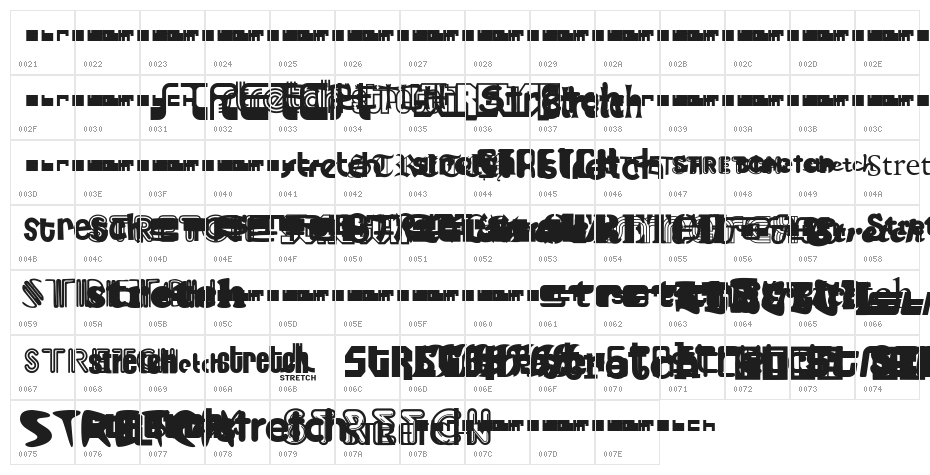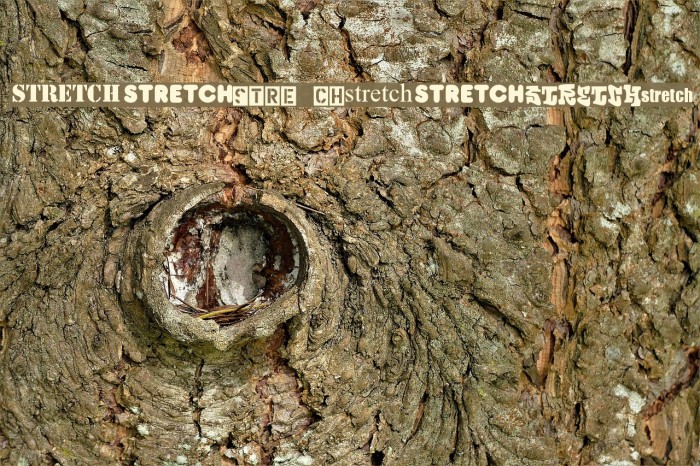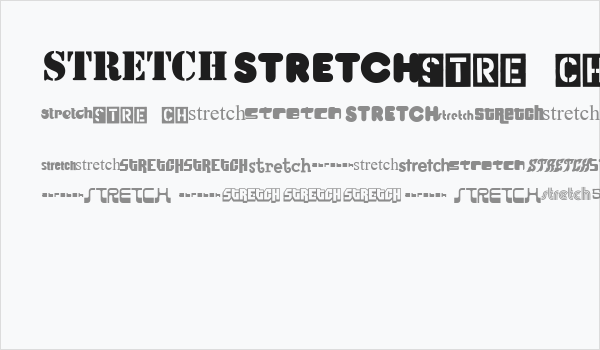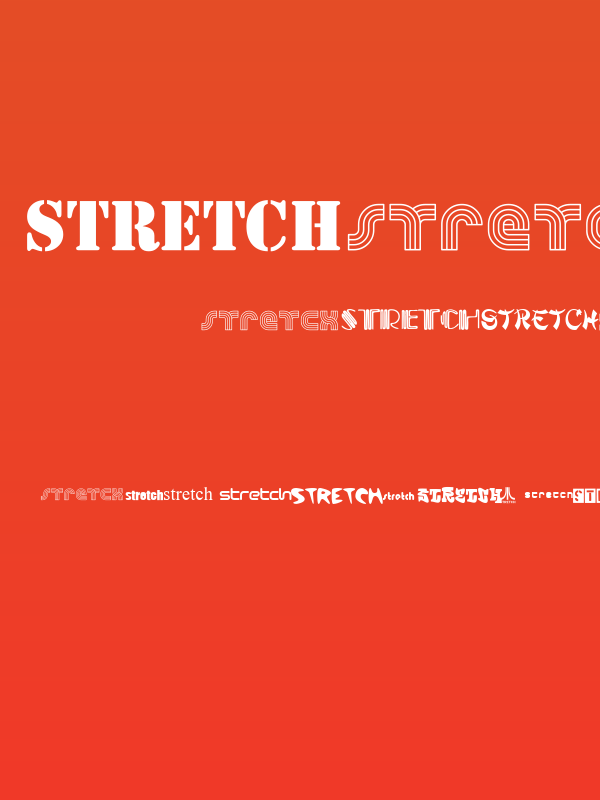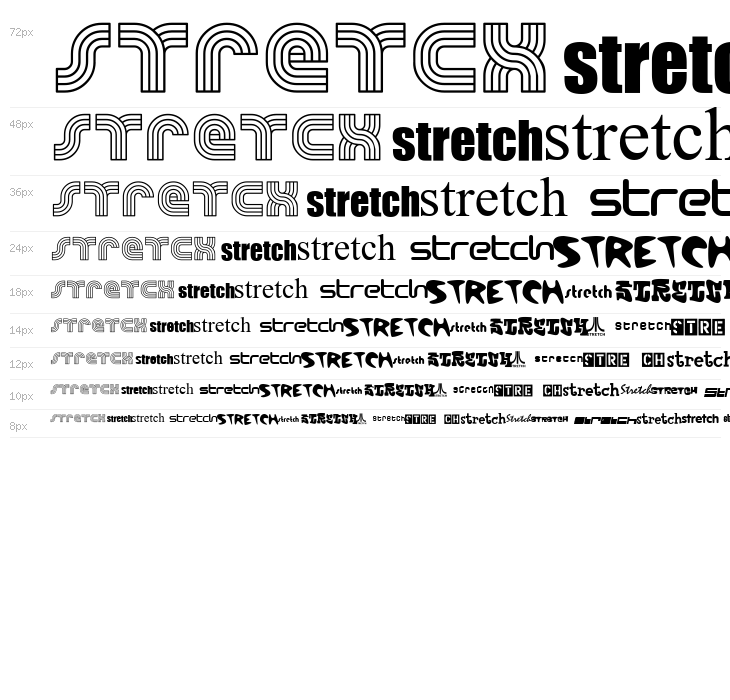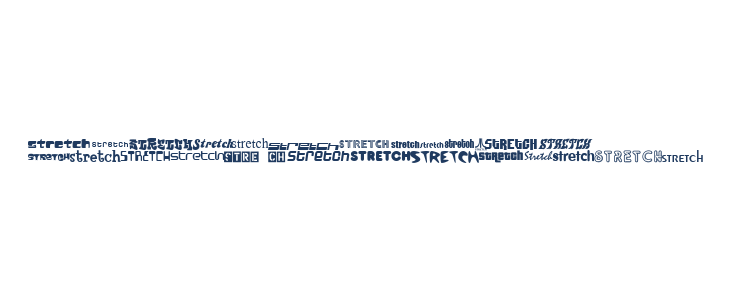
Stretch Font
| Lățime | Expanded |
| Proiecte propuse | Ideal for creative projects such as posters, album covers, and branding materials that require a bold and artistic touch. |